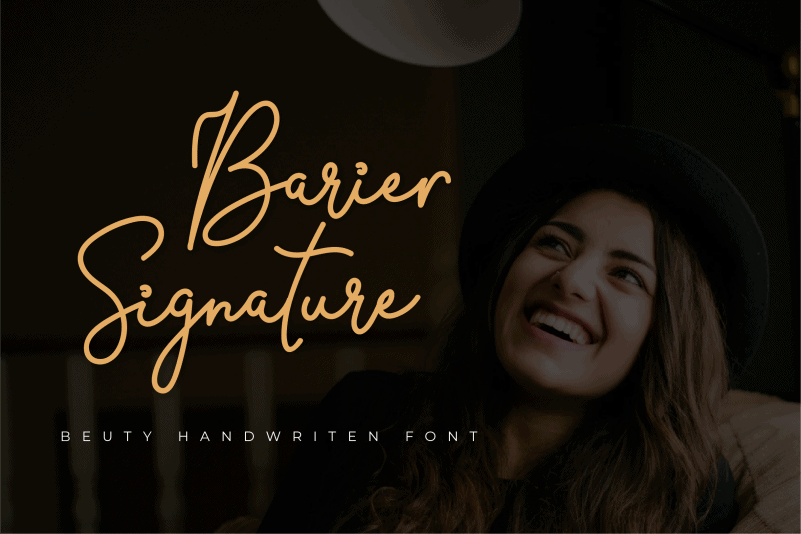
Barier Signature Script Font
A fonte ‘Barier Signature Script Font’ é uma escolha perfeita para aqueles que desejam adicionar elegância natural a seus projetos digitais. Com um design fluido e delicado, esta fonte assinatura se adequa perfeitamente a diversos usos, desde cabeçalhos de cartas até o layout do seu site pessoal. Seu designer, twinletter, comprou o conceito de elegância para transformar em uma verdadeira font de escrita à mão única e excepcionalmente viva. A versatilidade desse tipo de font permite que os criadores de materiais multipliquem sua estética, tornando-a perfeita não apenas como um título sofisticado, mas também para criar identidades corporativas autênticas e cartões de visita elegantes. Seja você uma designer gráfica procura dar um toque personalizado a suas criações, ou se você é um amante de design que busca incorporar esse elemento elegante em seu site pessoal, ‘Barier Signature Script Font’ certamente atenderá suas necessidades.